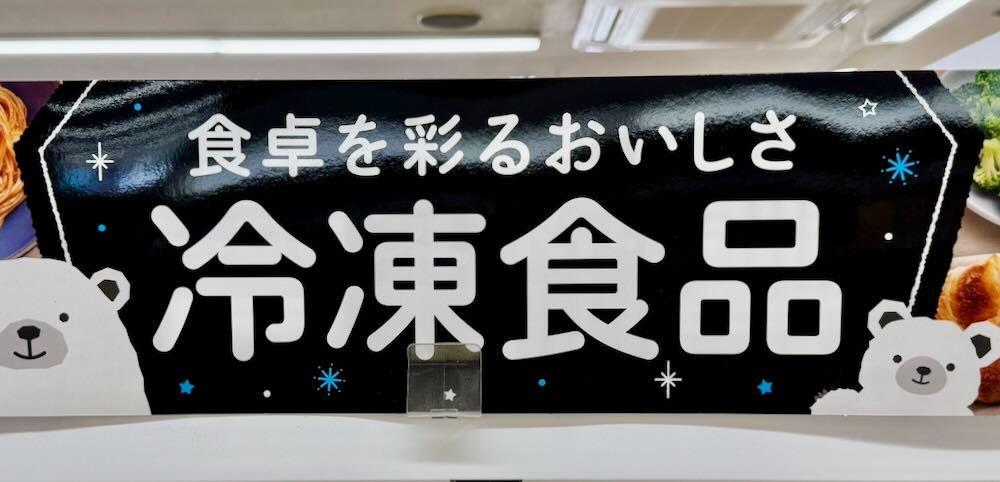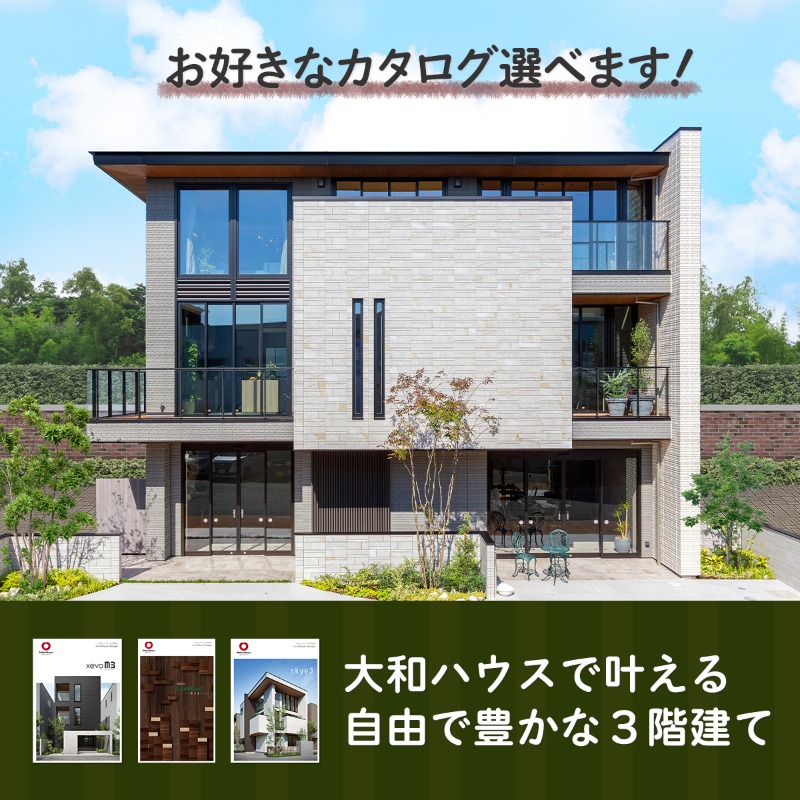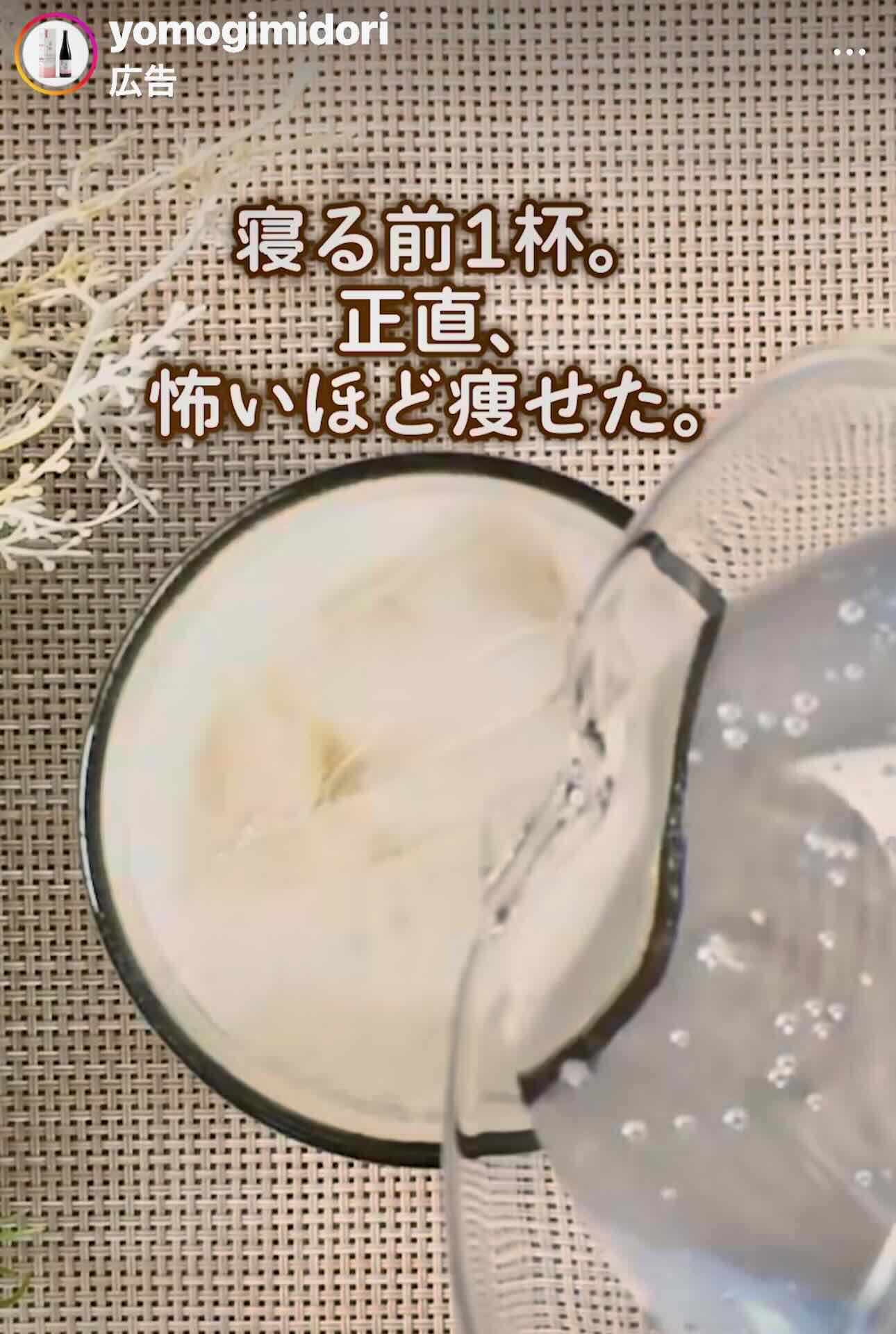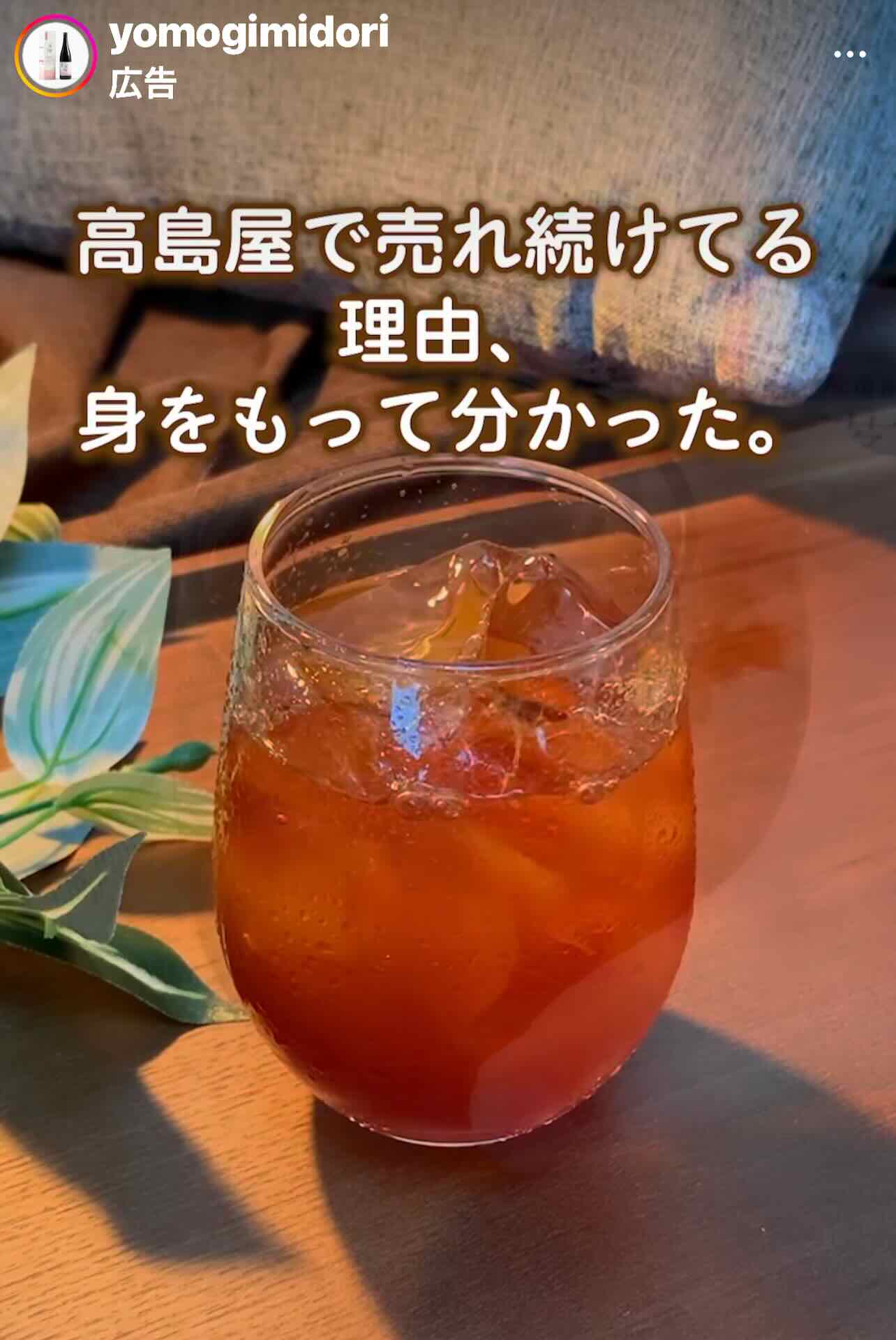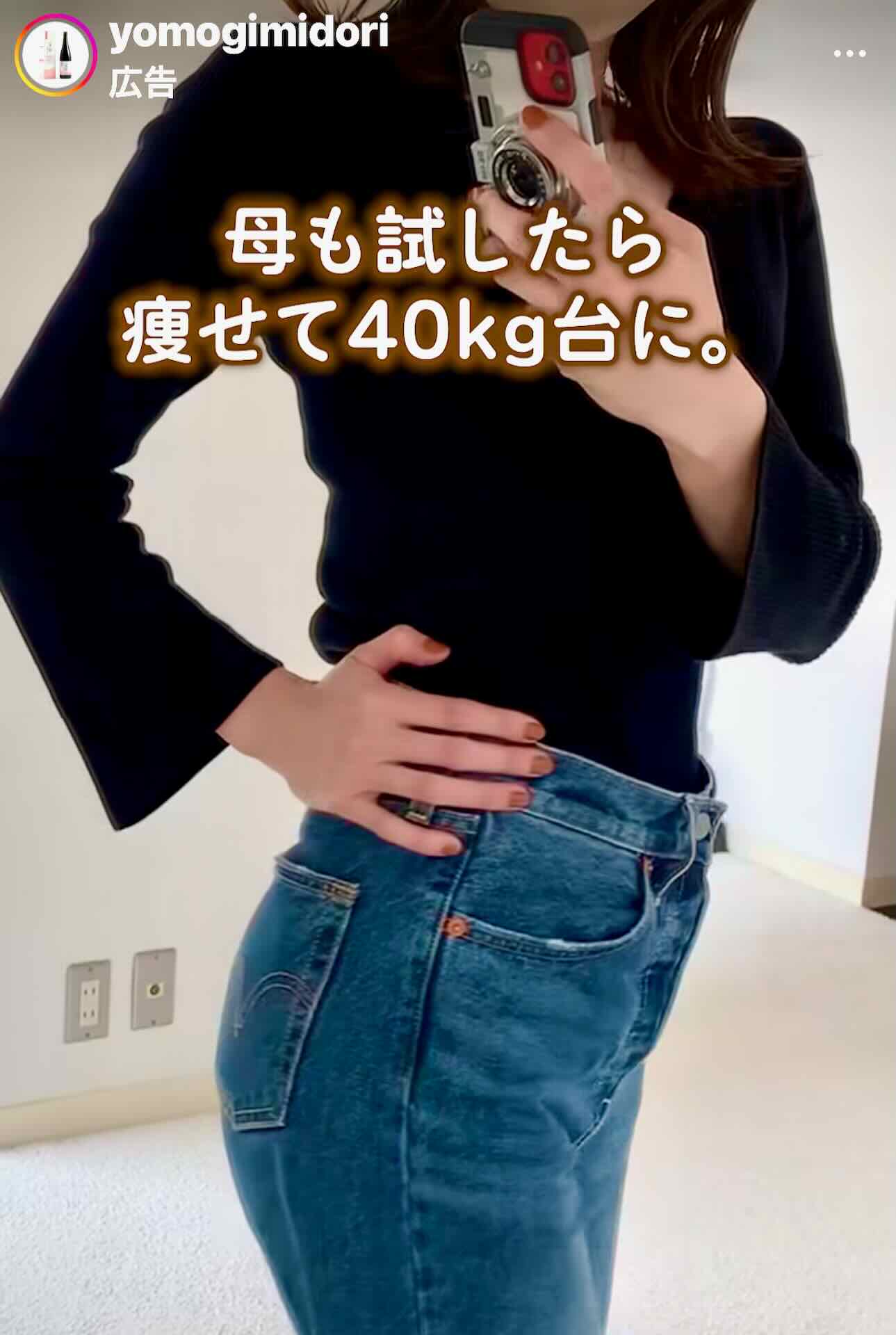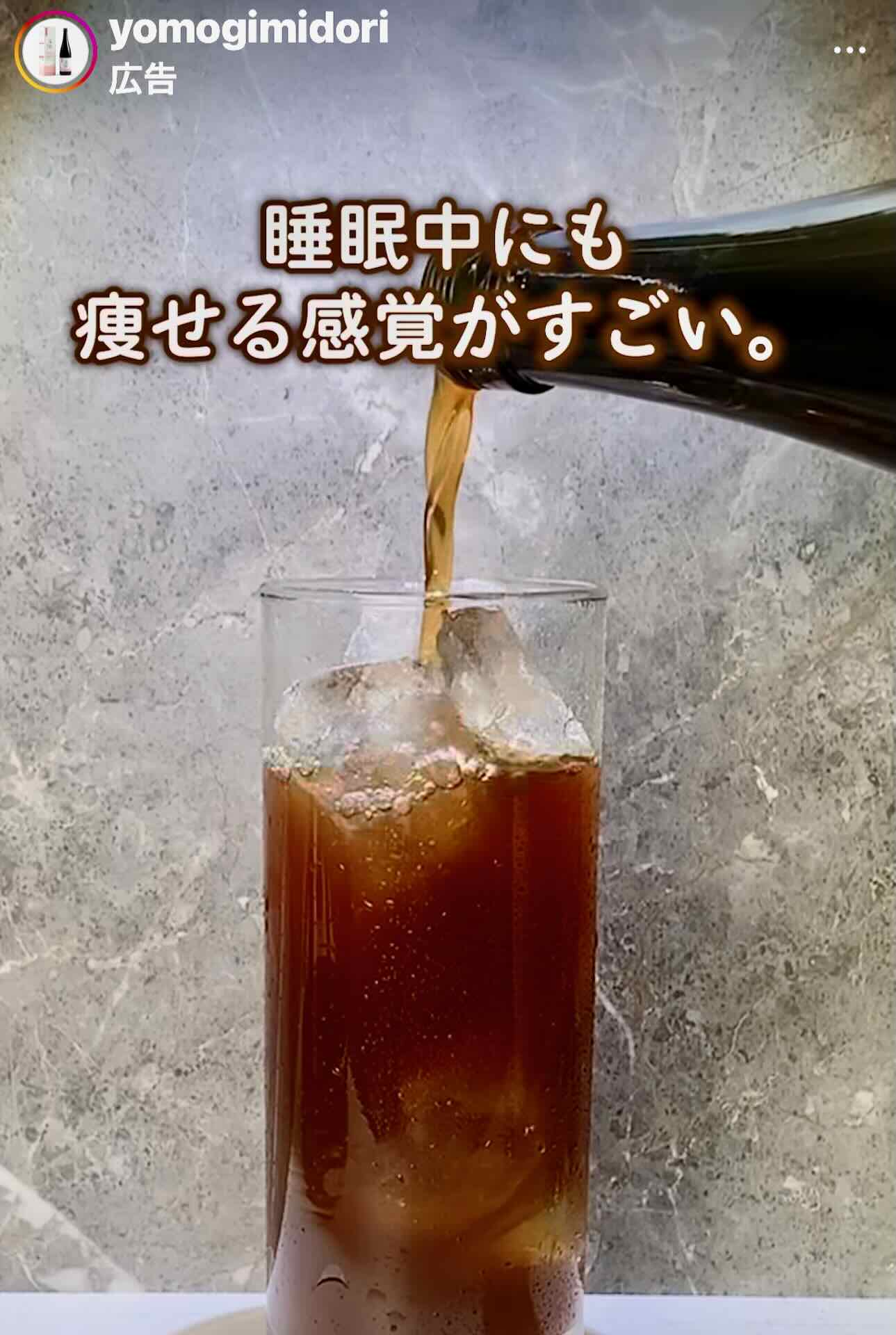
レラ・キャピレラ・ニタラゴレラ・墨東レラ・わんぱくレラ
JTBの「にっぽんの祭り・花火特集」
墨東レラ-6かな?
レラは、クセのないプレーンな丸ゴシック書体。
あまり目立つことはないが、言葉の意味に余分なイメージを付けず、やさしく伝えてくれる…。
すこし平べったく変形されている。
全体画像。
このフォントは墨東レラ。
健康食品のようだ。
これも。
まだある。
もうひとつ。
墨東レラ5の使用例。
親しみやすい丸ゴシックの漢字と、真面目で安心なイメージのかな書体「墨東丸」が、住宅という高価な商品の広告にうまくハマっている気がする。
墨東レラの使用例。
セブンイレブンの冷凍食品コーナー。
百均で見かけた「墨東レラ」です。
写真に写ってる文字はすべて墨東レラですが、機械的に太らせてるところがありますね…。
アイス de ヤクルト
この書体は、墨東レラ。